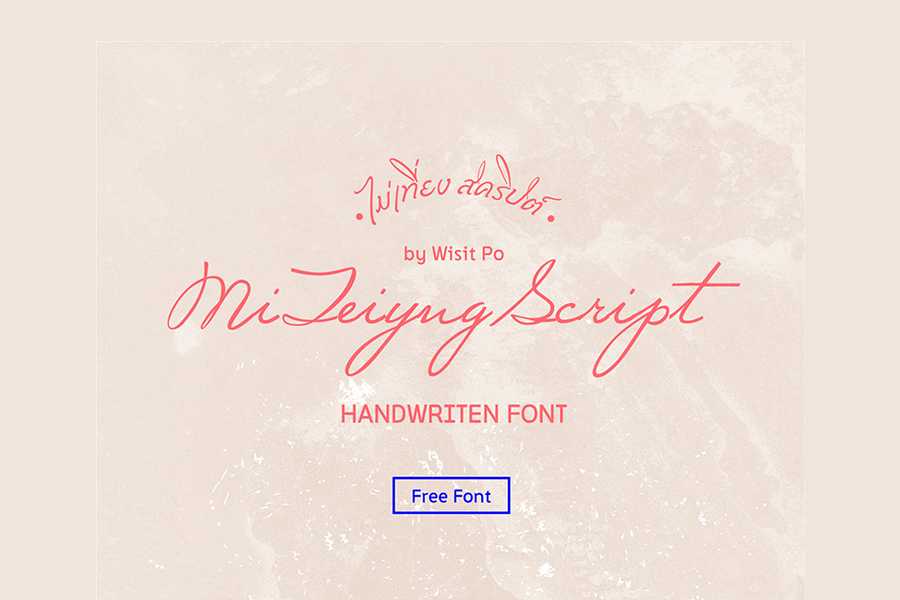
Mi Teiyng Script Font – Download Grátis
Mi Teiyng Script Font é uma tipografia que transmite a beleza e a originalidade do legado tradicional da cultura oriental asiática. Embora seja uma fonte de script, também é uma das fontes mais únicas e autenticamente escrita que você pode encontrar. Esta fonte foi desenvolvida em apenas um peso e estilo bison, mas é perfeitamente adequada para textos de tamanho maior. A Mi Teiyng Script Font é versátil e adequada para uma variedade de projetos, incluindo cartões de correspondência, embalagens, logotipos, panfletos, convites e muito mais.